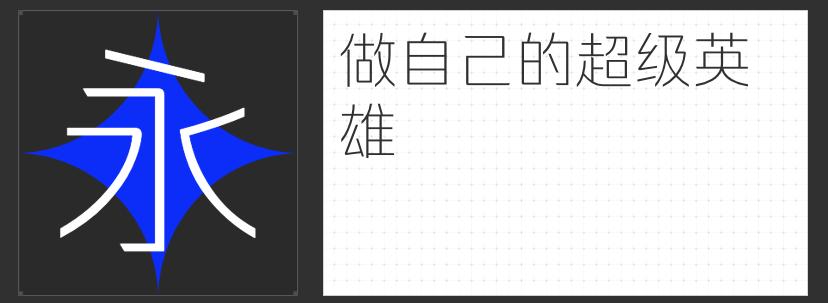
内嵌字体的品质之选:四款兼具美学与功能的字库推荐
在数字化内容呈现中,内嵌字体的选择直接影响着视觉体验的完整性与专业性。一款优秀的内嵌字体需兼顾屏显适配性、多场景通用性及文化内涵的传达。本文精选四款风格迥异却同样适合内嵌场景的精品字库,从现代黑体到古典宋韵,为不同需求的设计提供专业解决方案。
一、励字志向黑简 超粗
作为圆体与黑体融合的创新之作,励字志向黑简 超粗通过外圆角设计打破传统黑体的生硬感,在保持字面充实、结构稳定的同时,赋予笔画灵动的呼吸感。其笔画粗细经过精密计算,确保在高分辨率显示屏与移动端小字号场景下均能呈现清晰边缘,特别适合作为导航栏标题、品牌主视觉等核心信息载体。圆角与直线的微妙平衡,使其在科技、金融等强调专业感的领域中,既能传递权威感又不失人文温度。
二、励字超级勇士简 特细
以特细字重为核心设计的励字超级勇士简,通过匀称的中宫布局与清爽的笔画处理,构建出极简主义的视觉语言。其笔画粗细仅相当于常规字体的1/3,却在屏显时保持零断线、无毛刺的精致效果。这种"隐形的力量感"使其成为信息密集型界面的理想选择——无论是数据看板、长文本段落还是多语言排版,特细字重都能在有限空间内实现最大化的信息承载,同时通过流畅的字态维持视觉舒适度。
三、励字仿宋简繁
源自宋版刻书的励字仿宋简繁,将楷书的书写韵律与宋体的印刷特性完美融合。其笔画粗细均匀却暗含提按变化,横竖转折处保留手工雕刻的刀痕质感,在数字界面中重现古籍的典雅气息。作为内嵌字体,它既能独立呈现诗词歌赋等文化内容,也可作为正文的点缀字体与黑体形成对比。
四、励字书宋简繁
严格遵循传统宋体比例的励字书宋简繁,通过横细竖粗的经典结构传递出庄重肃穆的视觉信号。其笔画起收处的三角装饰经过数字化优化,既保留了木版印刷的古朴韵味,又消除了传统宋体在屏显时易出现的锯齿问题。作为内嵌字体,它特别适合法律文书、学术著作等需要权威感的场景,横竖对比的强烈节奏感也能有效引导阅读视线,提升长文本的可读性。
这四款字体通过不同的设计哲学,共同构建起内嵌字体的品质标准,为数字时代的视觉表达提供了丰富而专业的选择。